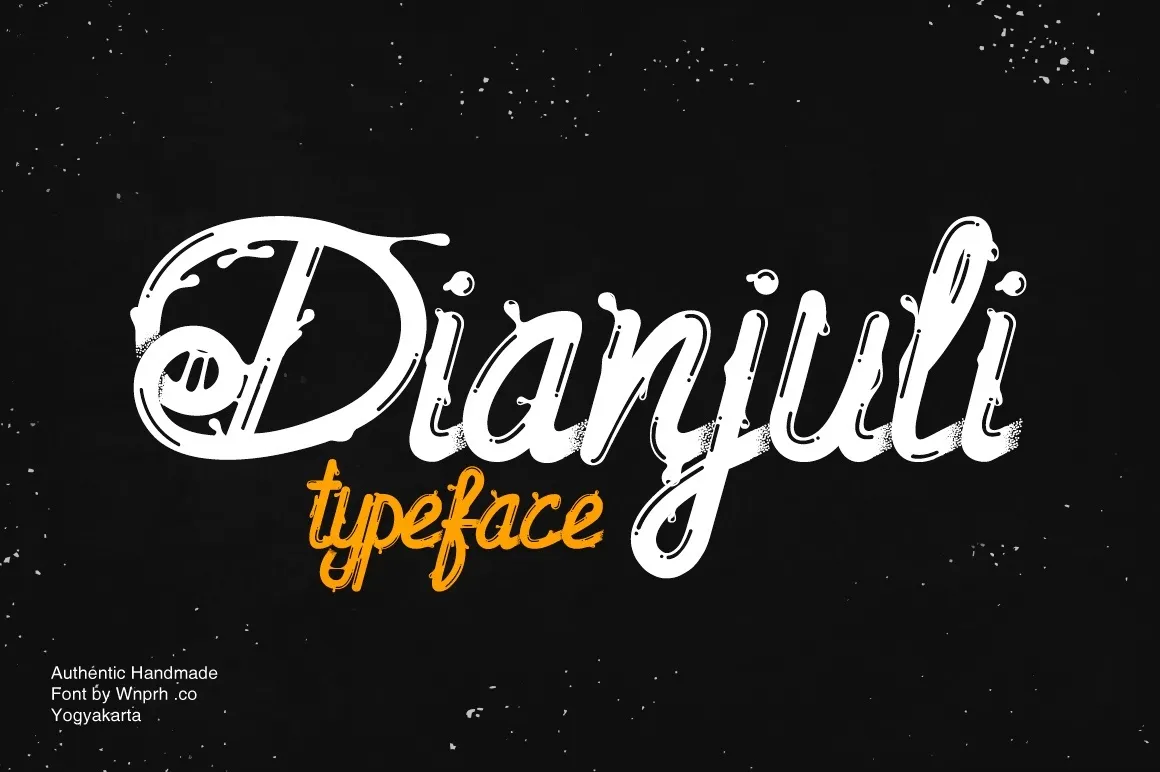
Dianjuli é uma tipografia à mão livre inspirada nos estilos de arte urbana, tatuagem e graffiti, criada para designers que desejam criar murais, headlines, logotipos e até mesmo roupas ou calçados personalizadas. O designer Hamilton capturou a essência da Dianjuli em um estilo único e customizável, feito especialmente para quem deseja uma fonte com um toque de arte manual que combina rusticidade e graça. Se você está procurando por uma fonte moderna e vibrante, que adiciona um toque especial a qualquer projeto gráfico, Dianjuli é perfeito. Suave o suficiente para ser usado em textos menores e forte o bastante para headlines, esta fonte é fácil de usar em qualquer software ou dispositivo. Não apenas é uma excelente opção para design de logotipos e ilustrações digitais, mas também oferece um toque autêntico aos designs impressos, tornando-a perfeita para a criação de roupas e acessórios personalizados.